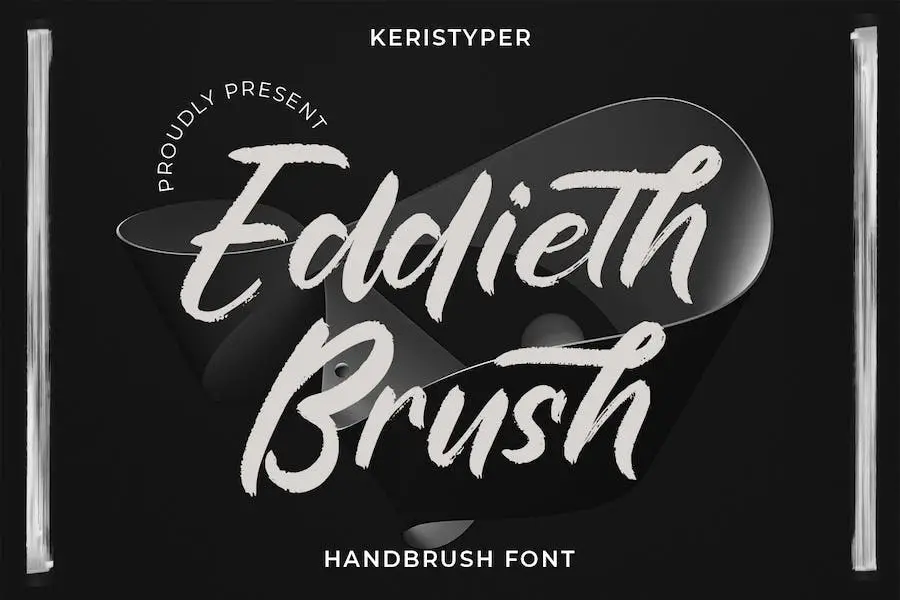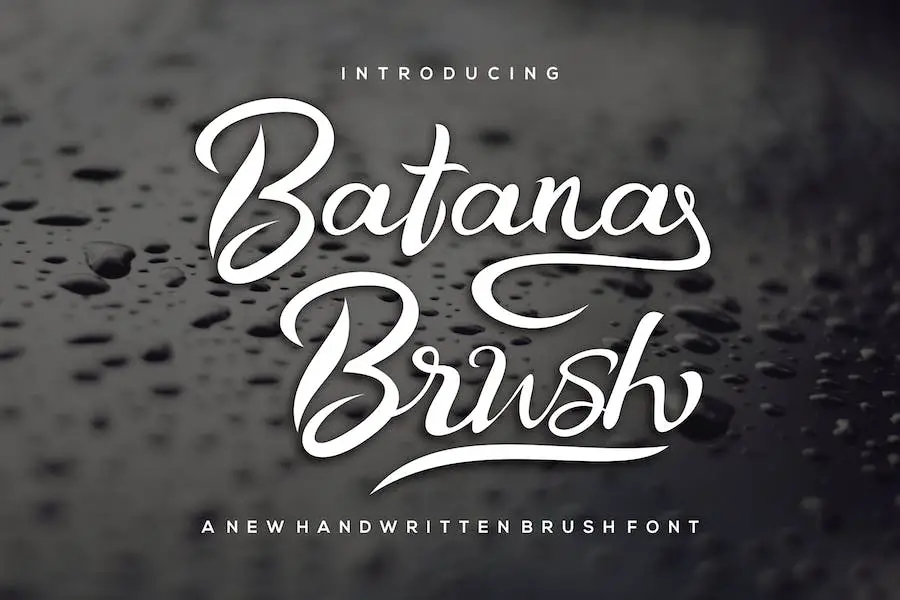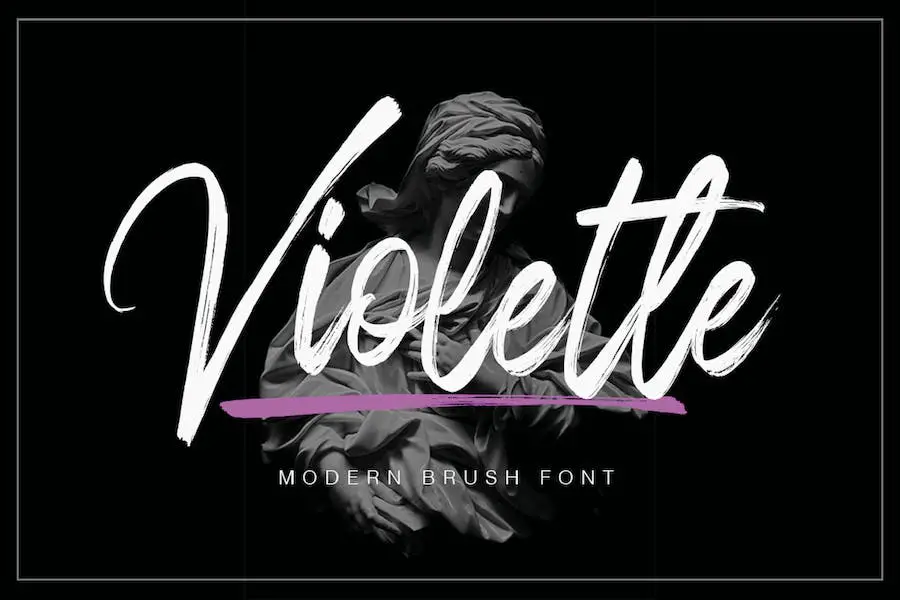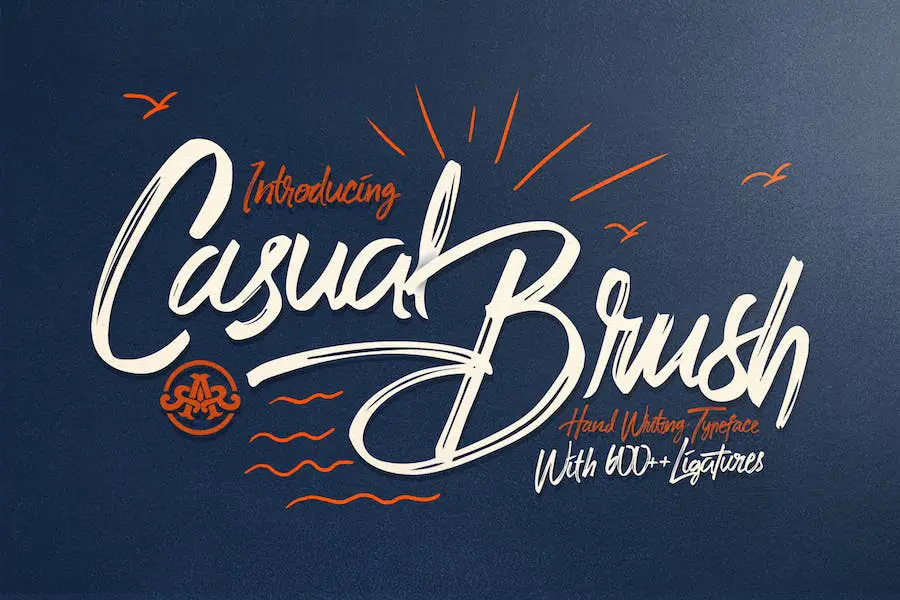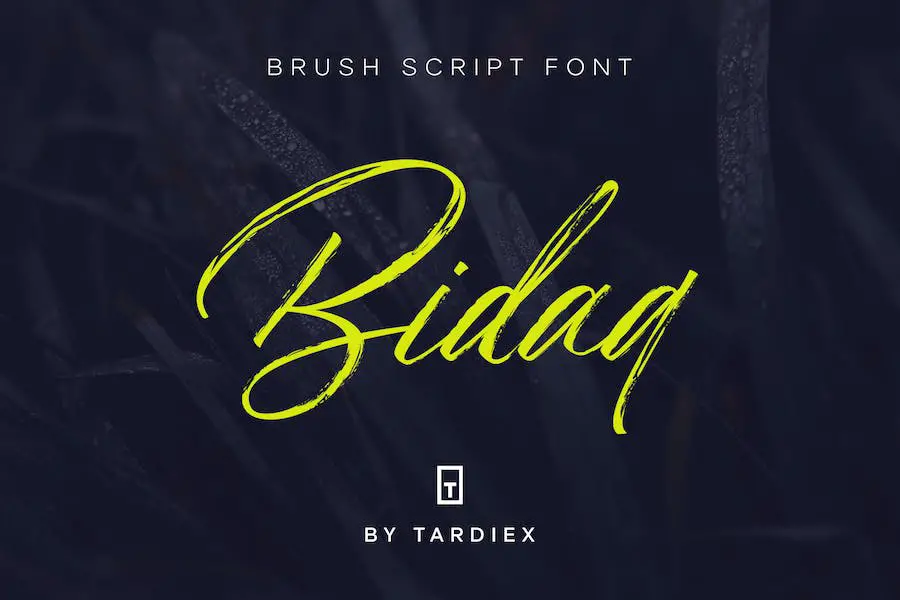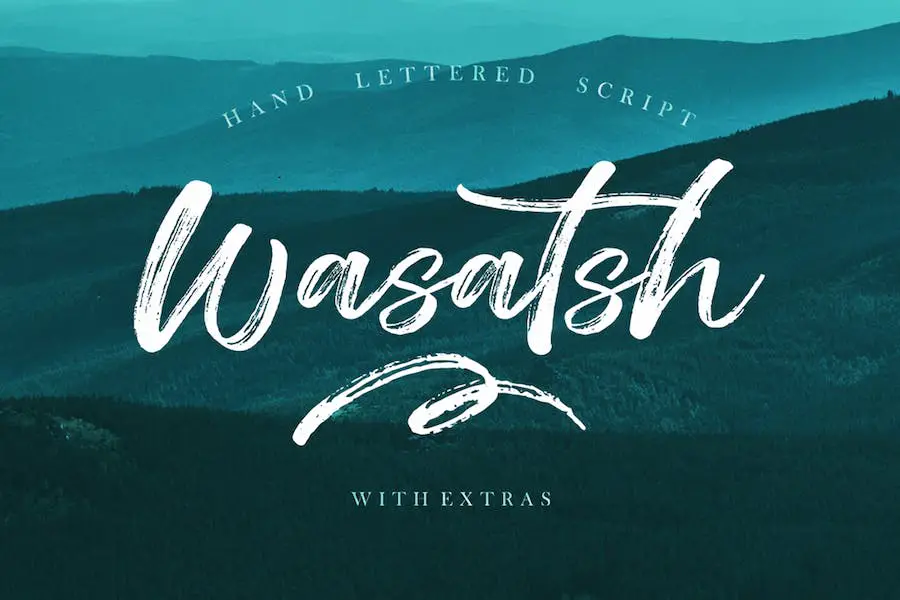
37 meilleures polices de pinceaux 2023 (gratuites et premium)
Publié: 2023-07-26Êtes-vous un graphiste à la recherche de la police de pinceau parfaite pour rehausser la conception de votre projet? Ou peut-être êtes-vous simplement curieux de connaître les meilleures polices de pinceaux disponibles ? Quoi qu'il en soit, vous êtes au bon endroit.
Dans cet article de blog, nous explorerons les 37 meilleures polices de pinceaux qui peuvent ajouter une touche de créativité et d'unicité à vos conceptions.
Maintenant, vous vous demandez peut-être pourquoi les polices de pinceau valent la peine d'être envisagées. Eh bien, voici un petit aperçu pour vous : les polices de pinceau ont acquis une immense popularité ces dernières années en raison de leur capacité à ajouter une touche organique et artisanale à n'importe quel design.
Avec leurs traits texturés et leurs caractères expressifs, les polices de pinceau peuvent injecter de la personnalité et du charme dans les logos, les supports de marque, les graphiques de médias sociaux, etc. Et la meilleure partie ? Ils sont incroyablement polyvalents et conviennent à un large éventail de styles et d'objectifs de conception.
Alors préparez-vous à plonger dans cette collection de polices de pinceau triées sur le volet qui ne manqueront pas d'inspirer votre prochain projet de conception. De l'élégant et sophistiqué à l'audacieux et audacieux, nous avons ce qu'il vous faut.
Que vous recherchiez une police pour une affiche, un site Web ou même une invitation de mariage, vous trouverez la police de pinceau idéale pour améliorer votre projet et le faire ressortir.
Alors sans plus tarder, commençons et découvrons les possibilités infinies qu'offrent ces polices de pinceau !
Meilleures polices de pinceaux premium
Vous cherchez à ajouter une touche artistique à vos créations ? Ne cherchez pas plus loin que notre sélection des meilleures polices de pinceaux premium. Avec leurs traits expressifs et leur sensation artisanale, ces polices ne manqueront pas d'élever vos projets à un tout autre niveau.
Restez à l'écoute car nous vous présentons une collection organisée de polices qui enflammeront votre créativité et laisseront une impression durable. Prêt à faire passer vos créations au niveau supérieur ? Plongeons-nous et explorons ces polices de pinceau incontournables!
Brosse rocheuse
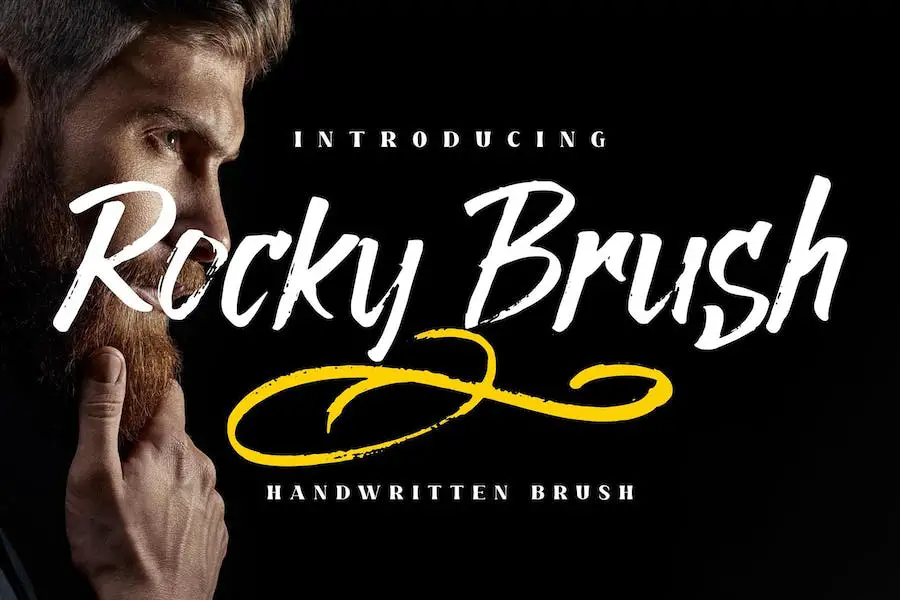
La police Rocky Brush est une option polyvalente et élégante pour les graphistes qui cherchent à améliorer la conception de leurs projets.
Grâce à sa capacité à se fondre de manière transparente avec divers formats, y compris les produits créatifs numériques et imprimés, cette police est un excellent choix pour les affiches, les publications sur les réseaux sociaux, l'image de marque et les projets personnels.
La beauté de Rocky Brush réside dans sa capacité à ajouter une touche d'élégance et de créativité à n'importe quel design. Ses coups de pinceau donnent un aspect authentique et artisanal, faisant ressortir vos créations du reste.
Amithène
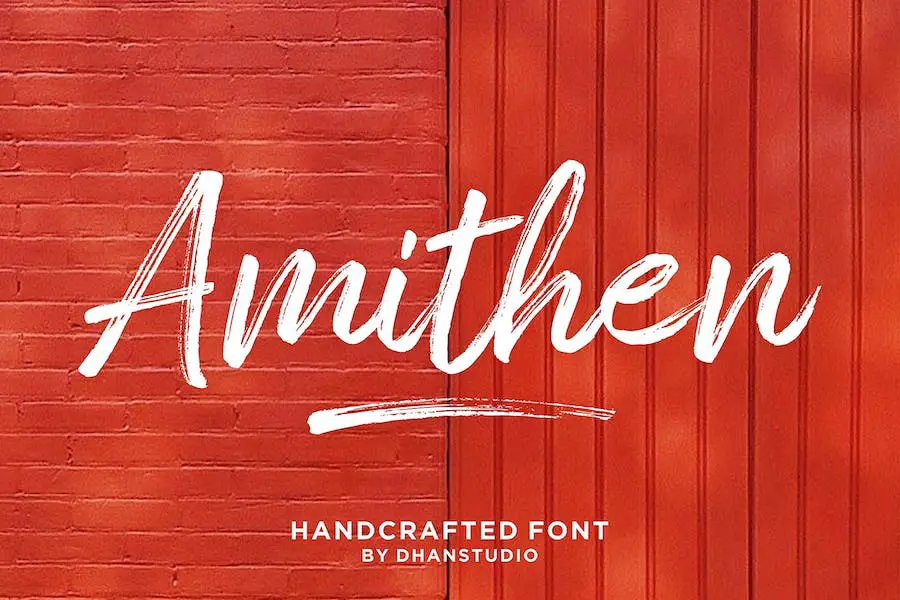
Amithen est une police de pinceau texturée qui adopte une approche contemporaine du design. Il a une sensation naturelle et faite à la main avec une ligne de base irrégulière, ce qui le rend parfait pour ajouter une touche unique à vos projets.
Cela fonctionne bien dans la conception de titres, que ce soit pour les vêtements, les invitations, les titres de livres, la papeterie, les citations, l'image de marque, les logos, les cartes de vœux, les t-shirts, les emballages, les affiches, etc.
La police comprend des lettres majuscules et minuscules, ainsi que la prise en charge de plusieurs langues, chiffres, ponctuation et ligatures. Avec Amithen, vous pouvez ajouter un élément élégant et artistique à vos créations.
Qindom
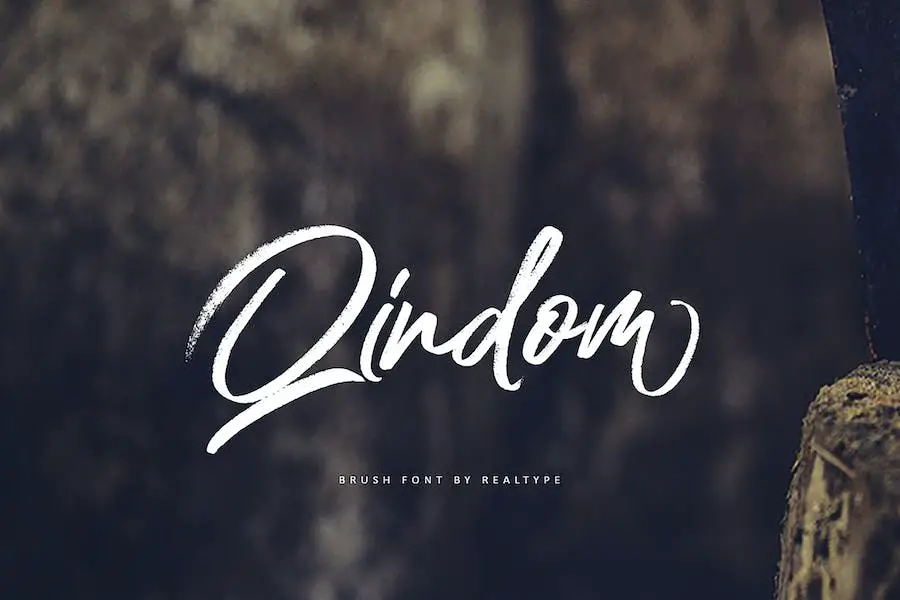
Qindom, une police de caractères au pinceau naturel, est la police idéale pour les graphistes qui cherchent à améliorer leurs projets avec un design frais et moderne. Créée à l'aide d'un stylo pinceau sec, cette police donne à vos créations une touche unique et artistique.
Que vous conceviez un tatouage, créiez des publications Instagram ou ajoutiez des lettres au pinceau à vos graphiques, Qindom a ce qu'il vous faut.
Nirmana
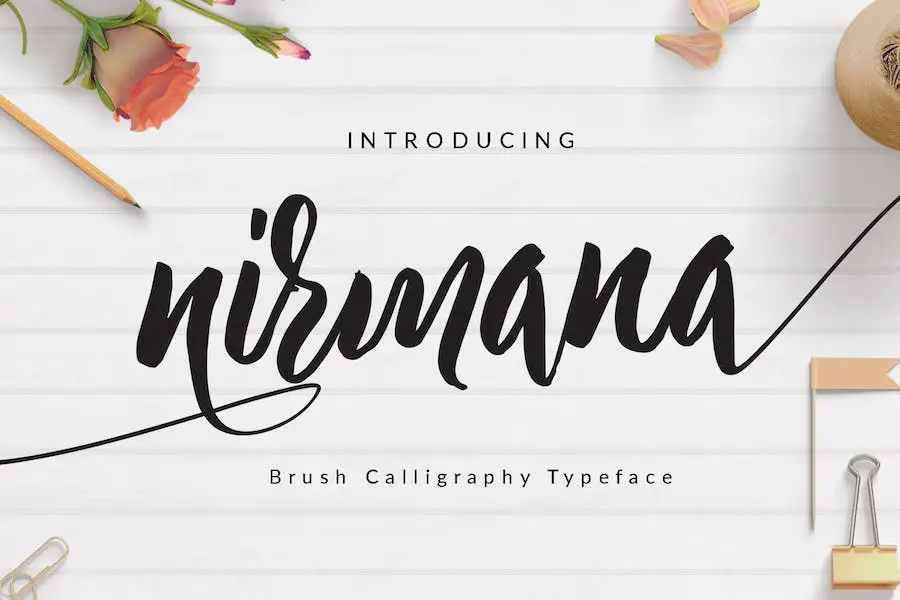
Nirmana est une police de calligraphie magnifique et polyvalente qui améliorera vos projets de conception graphique. Avec ses 326 glyphes et ses nombreux caractères alternatifs, il offre des possibilités infinies de créativité.